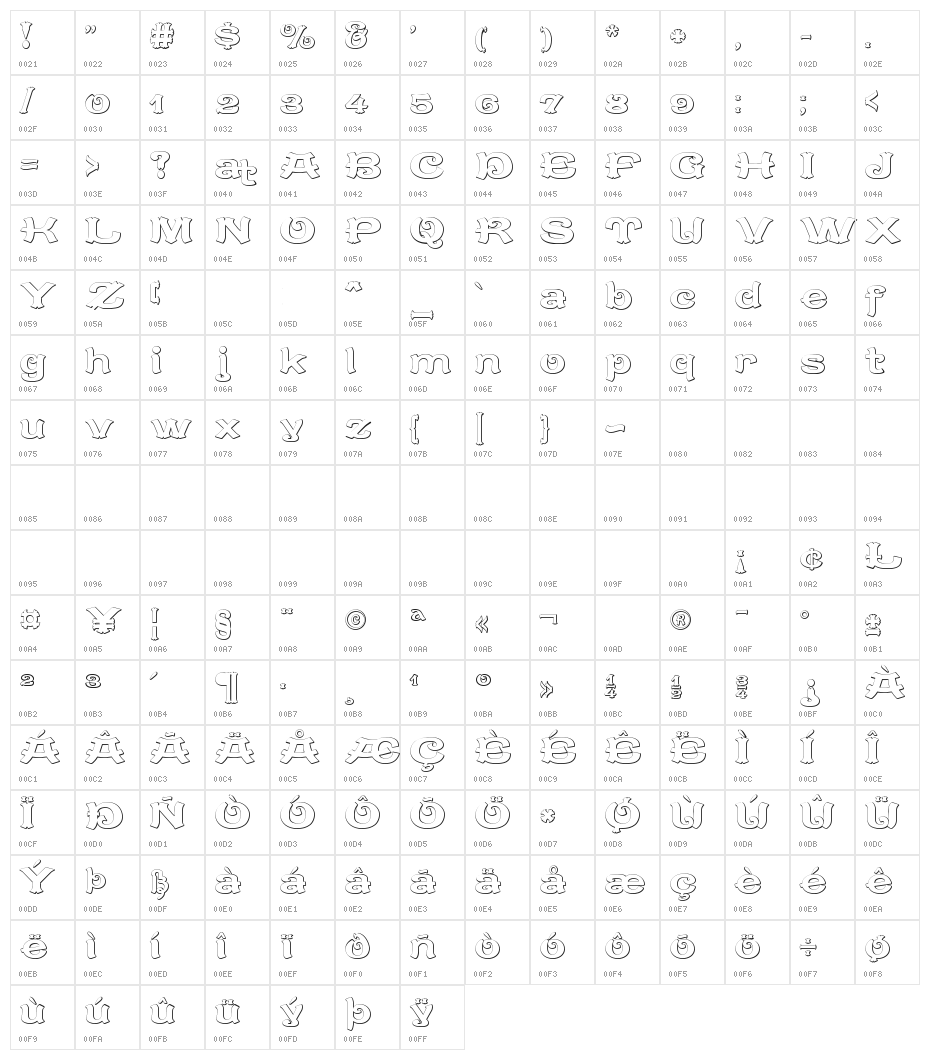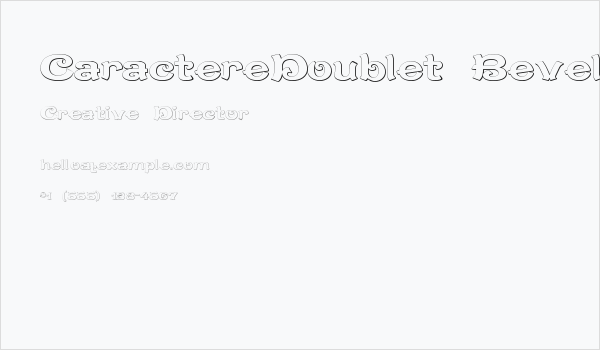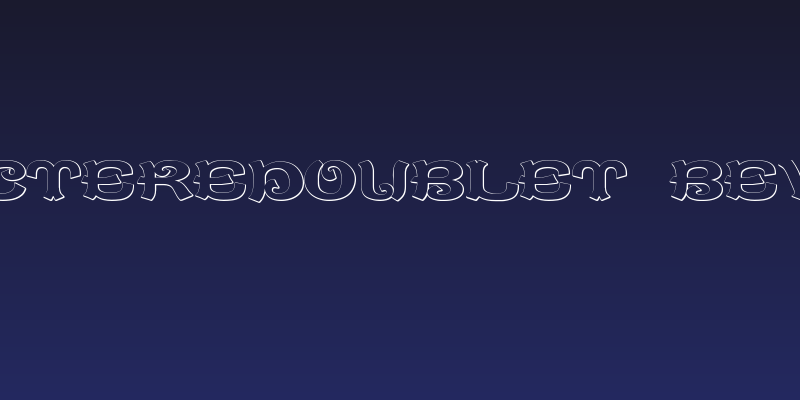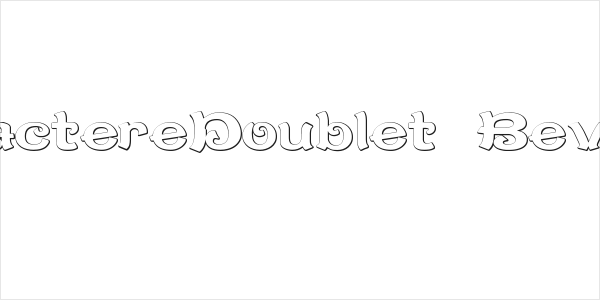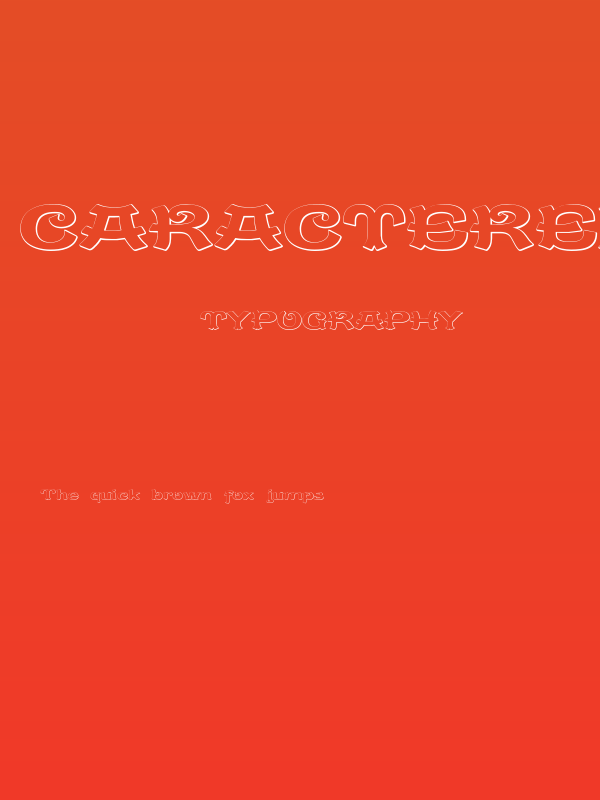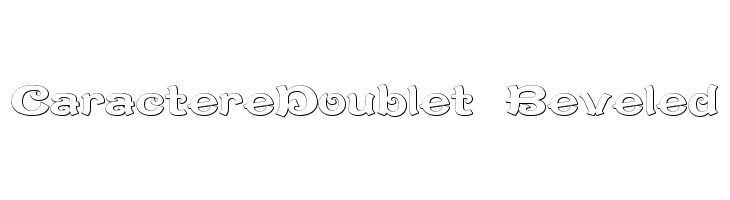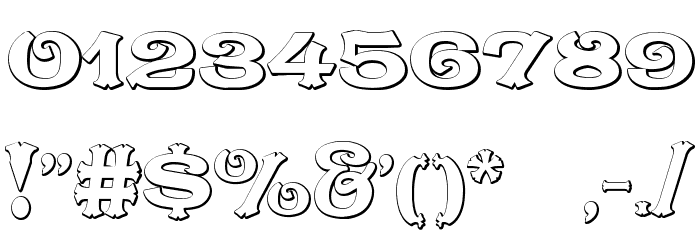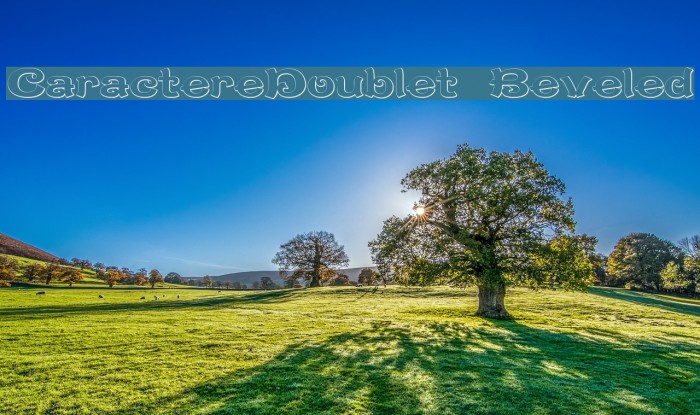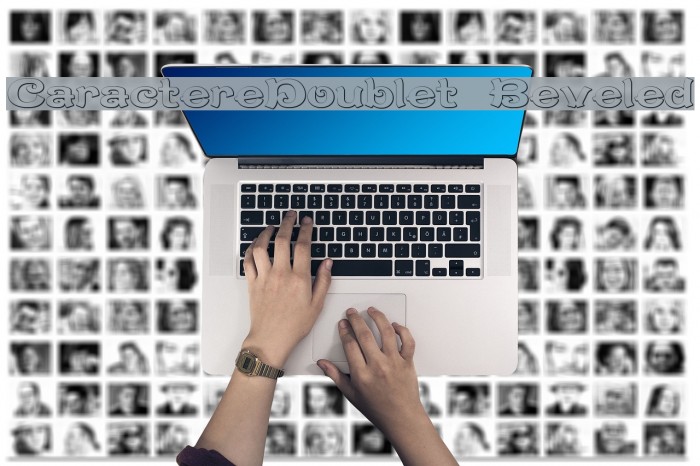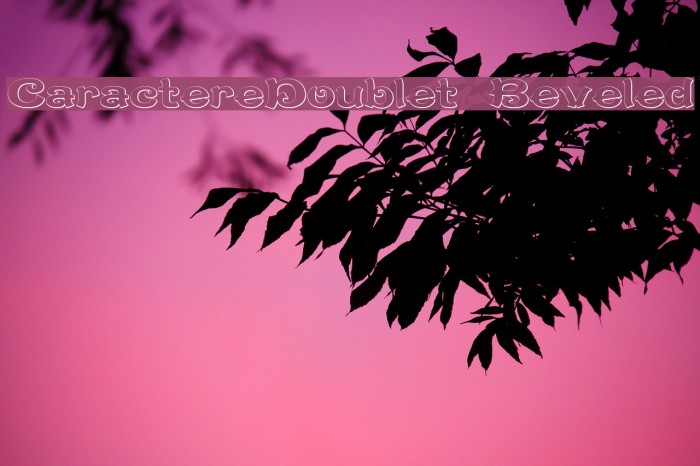
CaractereDoublet Beveled Font
| Projets proposés | Ideal for posters, logos, headlines, and any design requiring a striking, attention-grabbing typeface. |